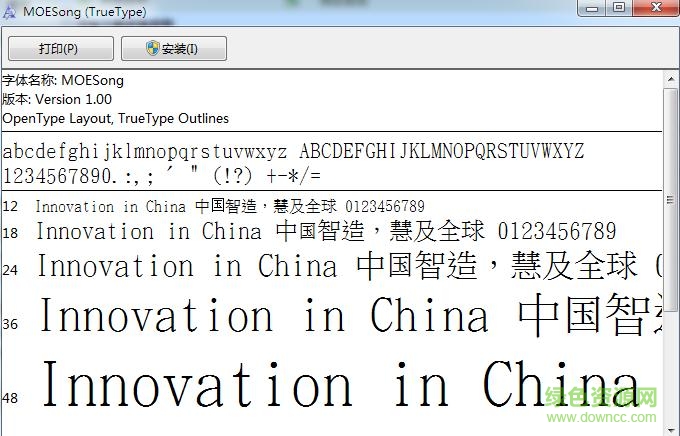
臺(tái)灣標(biāo)準(zhǔn)宋體是一款繁體宋體中文字體,字體較為瘦長(zhǎng),擁有楷體的筆型,各筆劃等粗,整體看上去工整、大氣,有需要的朋友歡迎免費(fèi)下載!
臺(tái)灣教育部標(biāo)準(zhǔn)宋體是一款臺(tái)灣地區(qū)使用的宋體字體,字身修長(zhǎng),工整秀麗,勻稱,筆畫(huà)挺拔,起落偏頓,橫斜豎直,粗細(xì)一樣,間隔均勻,常用于印刷。